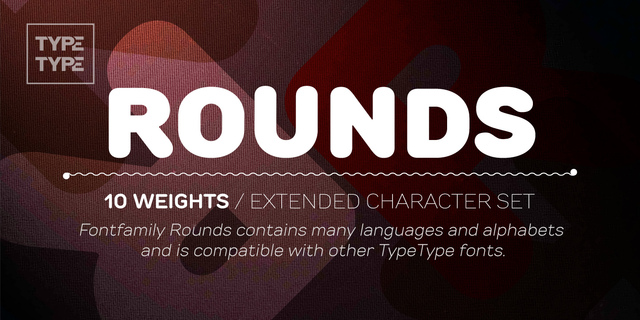
TT Rounds (10 шрифтов)
Rounds – шрифт с очень добрым и нежным характером. Самый популярный набор начертаний: тонкое, светлое, нормальное, жирное, сверхжирное и их наклонные версии. Шрифт сделан таким образом, чтобы он мог применяться как в кратких текстах (логотип или заголовок), так и в полосе набора (абзац текста или статья в газете). Область применения: детские книжки, кафе, упаковка, сайты, ценники, логотипы, реклама, косметика, игрушки. Оптимизирован для применения на сайтах, в мобильных приложениях и печатной продукции. Шрифт разработан Иваном Гладких в студии TypeType Fonts в 2014 году.